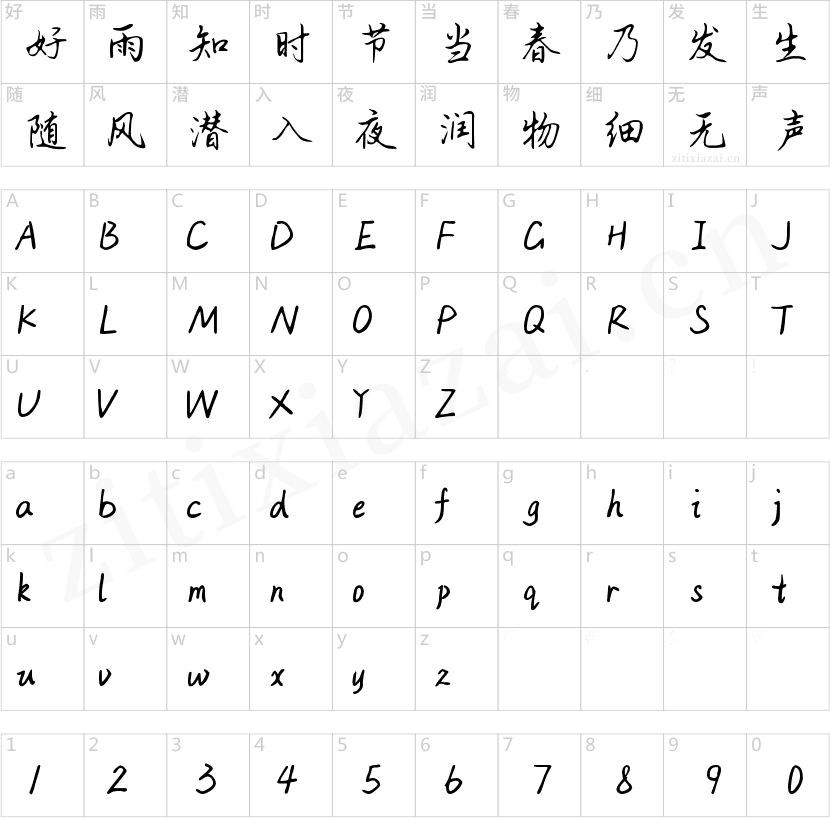
Aa银河绘日云月呢喃
Aa银河绘日云月呢喃,这款字体结构工整、笔画清晰,兼顾美观与易读性,适用于标题、正文、海报、包装、LOGO 等多种场景。字形优雅稳定,风格百搭耐看,适配日常排版与创意设计,让文字呈现更舒适、更具质感。Aa银河绘日云月呢喃一笔一画,皆是细节,以均衡的比例、流畅的线条打造舒适视觉体验,字形端正大气,风格简约现代。无论是商业设计、品牌宣传还是日常排版,都能轻松驾驭,让文字更有格调与力量。Aa银河绘日云月呢喃字体下载。
Aa银河绘日云月呢喃字体
Aa银河绘日云月呢喃是一款非常具有艺术性的字体,它的设计灵感来源于对古典艺术的研究,同时又融入了现代字体设计的元素。字形优美,笔画粗细变化自然,给人以大气、典雅的感觉。Aa银河绘日云月呢喃是一款既传统又现代的字体,它的设计充满艺术感,美观大方,实用性也非常强。无论是对于设计师还是对于普通读者来说,都是一种非常不错的字体选择。Aa银河绘日云月呢喃适合用于具有艺术感的场合,比如海报、宣传单张、书籍封面等。由于其字形流畅且具有动态感,也适合用于大量的文本排版,如报纸、杂志等。
Aa银河绘日云月呢喃详情